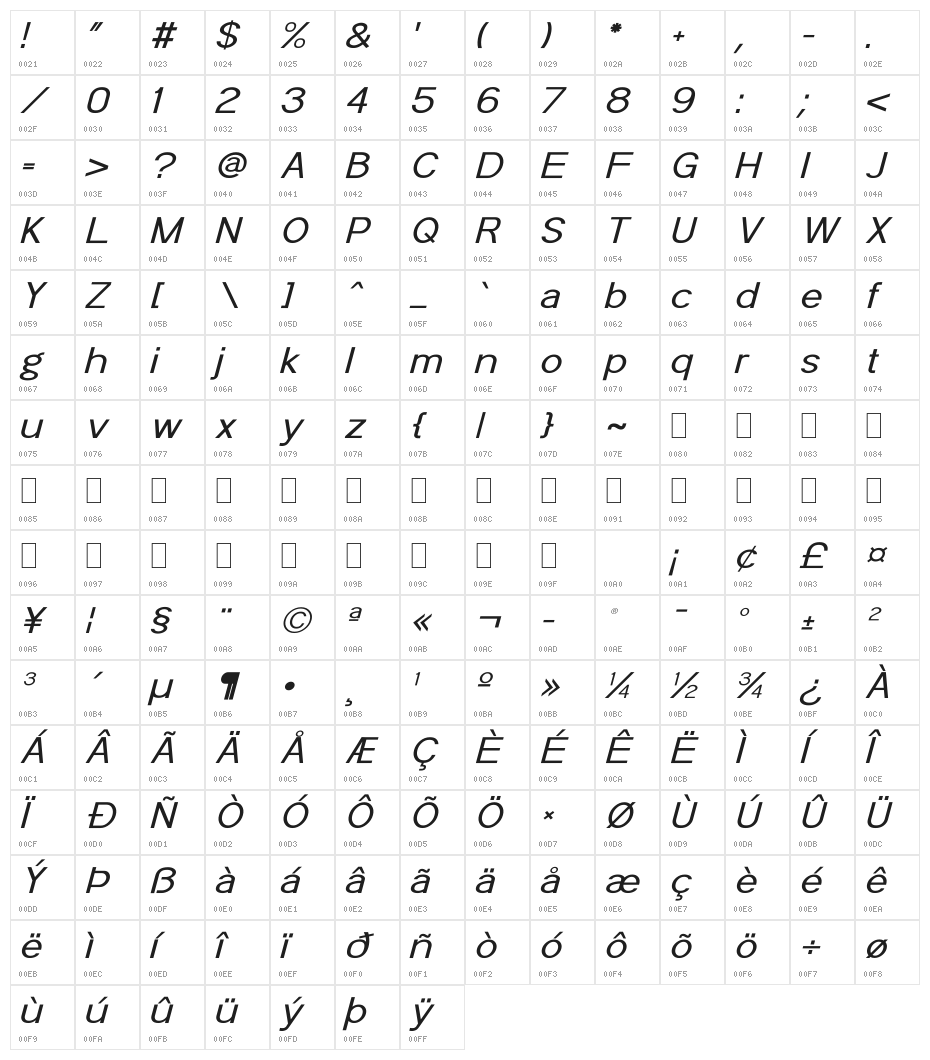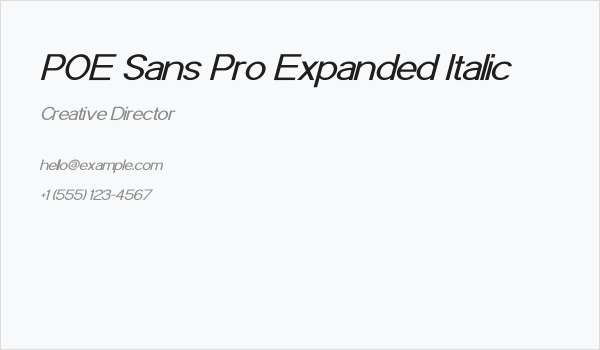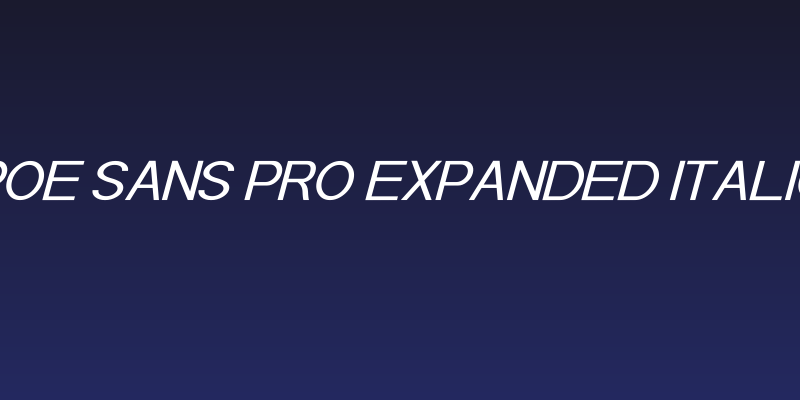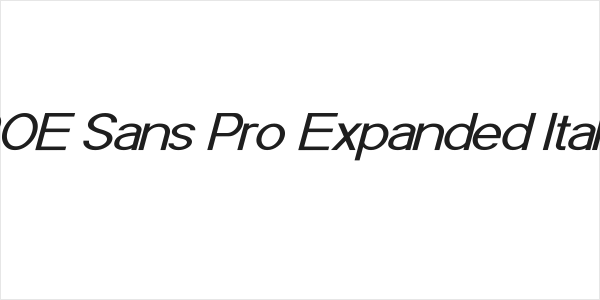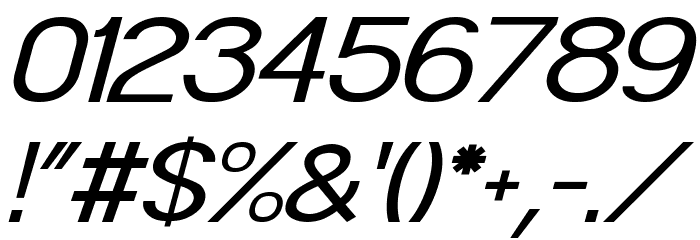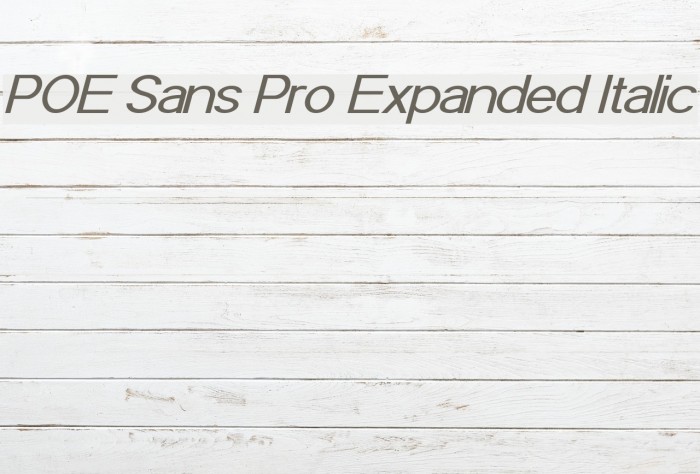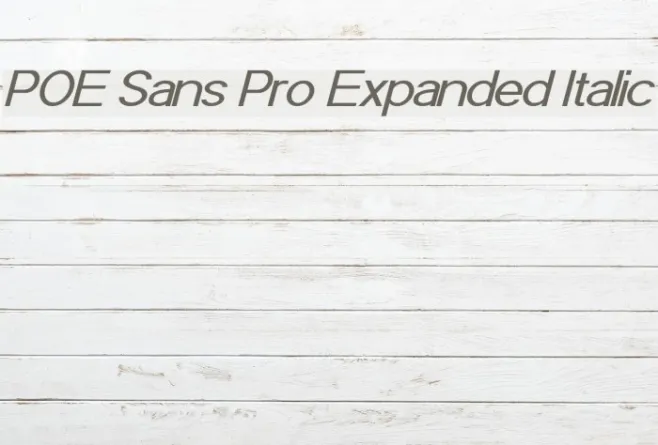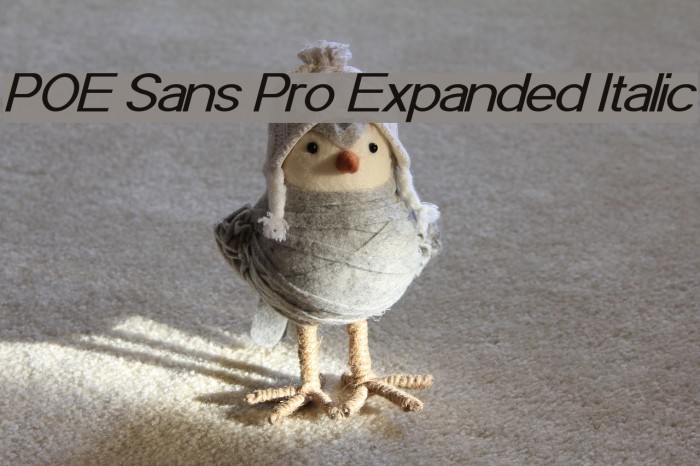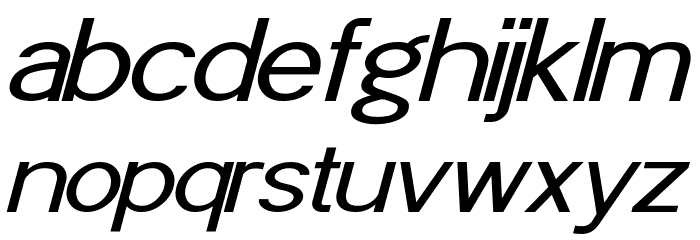
POE Sans Pro Expanded Italic Font
| Kategorien | Sans Serif |
| Breite | Expanded |
| Anwendungsfall | Headlines, Branding, Advertising |
| Vorgeschlagene Projekte | Ideal for branding, advertising, headlines, and digital media where a modern and elegant look is desired. |